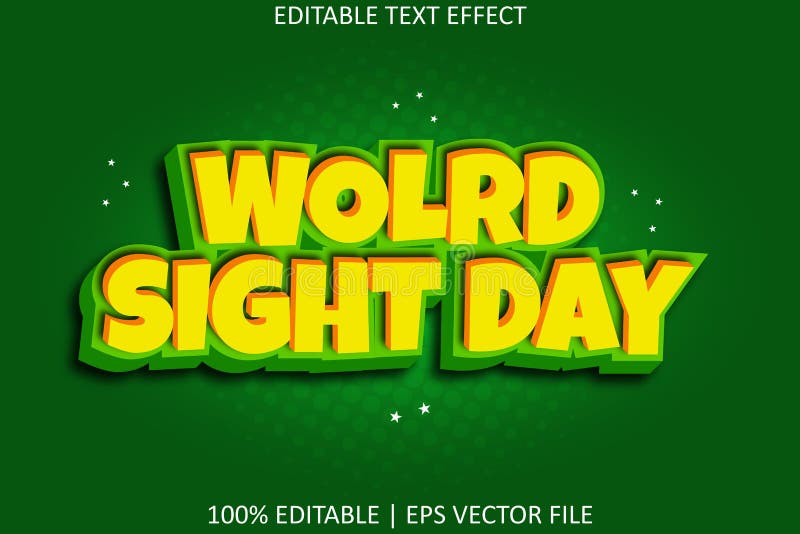
день просмотра с помощью мультфильма. это не шрифт. эффект шрифта для иллюстратора adobe. его нельзя открыть другим программным обеспечением. слова и шрифты все еще могут быть изменены